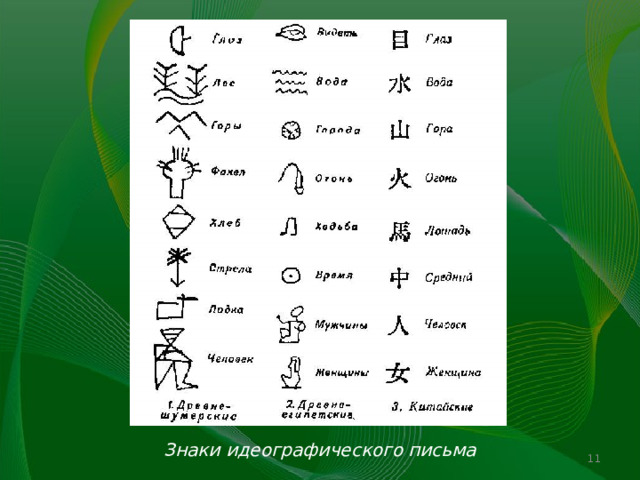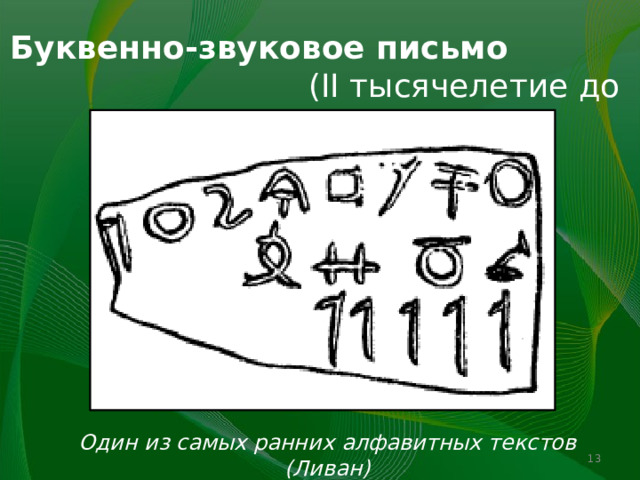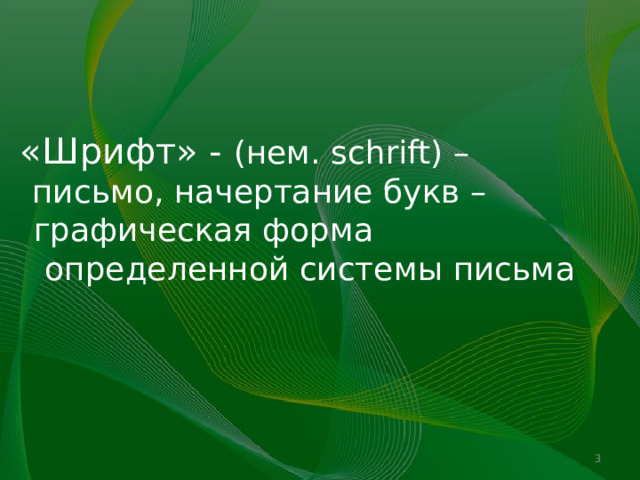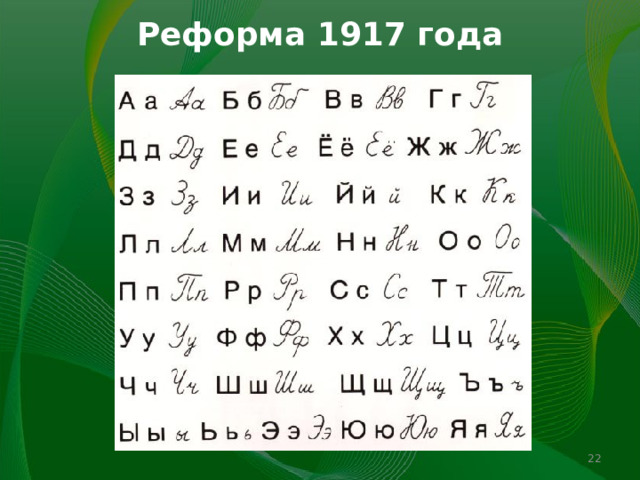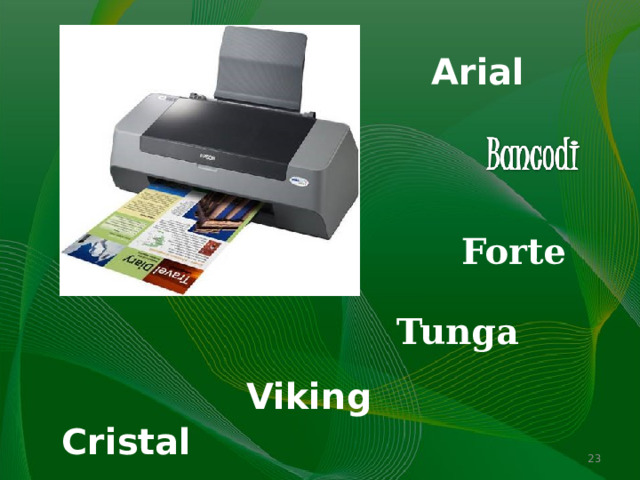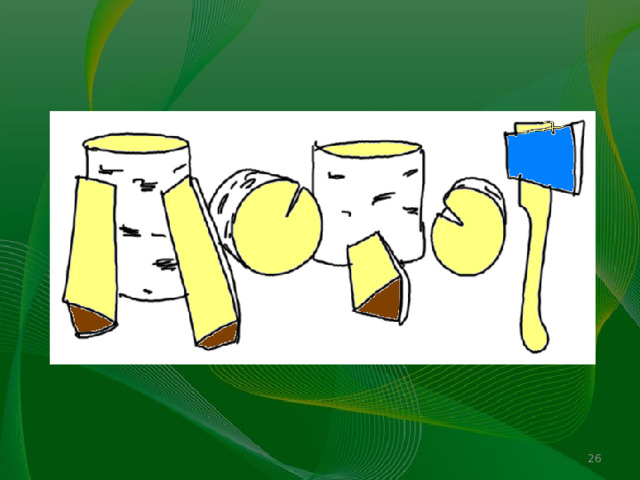
«Шрифт»
«Шрифт» - (нем. schrift) – письмо, начертание букв – графическая форма определенной системы письма
Назначение - передача информации в письменном виде во времени и пространстве
Бизон. Наскальная живопись
Виды письменности: Пиктографическое Идеографическое Слоговое Буквенно-звуковое
Виды письменности:
• Пиктографическое
• Идеографическое
• Слоговое
• Буквенно-звуковое
Пиктография (лат. pictus –«живописный» и от греч. grapho - пишу) -
Пиктография (лат. pictus –«живописный» и от греч. grapho - пишу) - "рисую-пишу» /рассказ в картинках/
Пиктография. Охота на оленей. Испания
Идеография - в перев. с лат . « пишу понятие» или «пишу идею»; иероглифы :
Идеография - в перев. с лат . « пишу понятие» или «пишу идею»;
иероглифы : "иеро" - "священный", "глифы" - "высеченный на камне". (IV-III тысячелетия до н. э.)
Знаки идеографического письма
Слоговое письмо (III-II тысячелетия до н. э.)
Слоговое письмо
(III-II тысячелетия до н. э.)
Буквенно-звуковое письмо (II тысячелетие до н. э.) Один из самых ранних алфавитных текстов (Ливан)
Буквенно-звуковое письмо (II тысячелетие до н. э.)
Один из самых ранних алфавитных текстов (Ливан)
Если взять большое слово,  Вынуть буквы, раз и два,  А потом собрать их снова,  Выйдут новые слова.  Поиграйте раньше с нами,  А потом играйте сами.  Вот из слова ГАСТРОНОМ  Вышел важный АСТРОНОМ, Вышел МАГ и вышел ГНОМ,  А за ними АГРОНОМ..  МОСТ построен на реке,  ГРОМ грохочет вдалеке,  С нижней палубы МАТРОС  От причала тянет ТРОС...  Сверху лётчику видна  Вся родная СТОРОНА.  ГАСТРОНОМ : астроном, маг, гном, агроном, мост, гром, матрос, трос, сторона, ас, нос, мор, ром, оса, нога, март, стог, мотор, сон, рот, морс, трон, март, нота, тор, рог, гора, нора,…
Если взять большое слово, Вынуть буквы, раз и два, А потом собрать их снова, Выйдут новые слова. Поиграйте раньше с нами, А потом играйте сами. Вот из слова ГАСТРОНОМ Вышел важный АСТРОНОМ, Вышел МАГ и вышел ГНОМ, А за ними АГРОНОМ.. МОСТ построен на реке, ГРОМ грохочет вдалеке, С нижней палубы МАТРОС От причала тянет ТРОС... Сверху лётчику видна Вся родная СТОРОНА.
ГАСТРОНОМ : астроном, маг, гном, агроном, мост, гром, матрос, трос, сторона, ас, нос, мор, ром, оса, нога, март, стог, мотор, сон, рот, морс, трон, март, нота, тор, рог, гора, нора,…
Один из первых алфавитов на Земле – финикийский. 11 в. до н. э.    Один из первых алфавитов на Земле - финикийский.
Один из первых алфавитов на Земле – финикийский. 11 в. до н. э.
Один из первых алфавитов на Земле - финикийский.
Древнегреческая надпись демонстрирует двустороннее направление строки. VII-VIII в.в. до н. э.
Кириллица и Глаголица IX в.
Кириллица /«Устава»/
Вязь XV в. «Полуустава»
Типография /Германия, XV в./ буквы-литеры
Типография
/Германия, XV в./
буквы-литеры
Основатель первой типографии в России - Иван Федоров.  Первая напечатанная книга – «Апостол» /1564 г./, вошедшая в историю книгопечатания и типографий мира
Основатель первой типографии в России - Иван Федоров.
Первая напечатанная книга – «Апостол» /1564 г./, вошедшая в историю книгопечатания и типографий мира
Реформа 1917 года
Arial Forte Tunga Viking Cristal
Arial
Forte
Tunga
Viking
Cristal
СОЛНЦЕ КНИГА ПОЛЁТ
СОЛНЦЕ
КНИГА
ПОЛЁТ